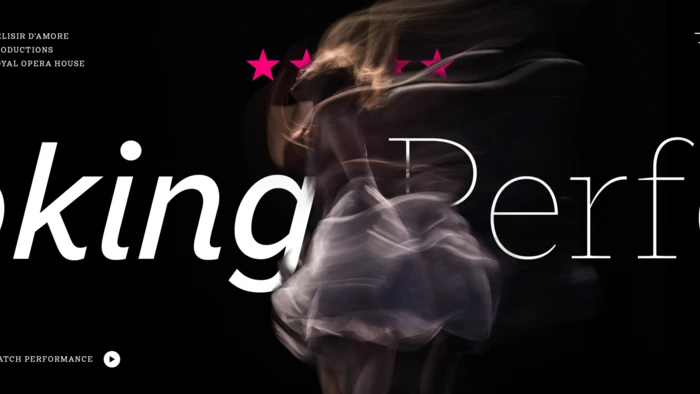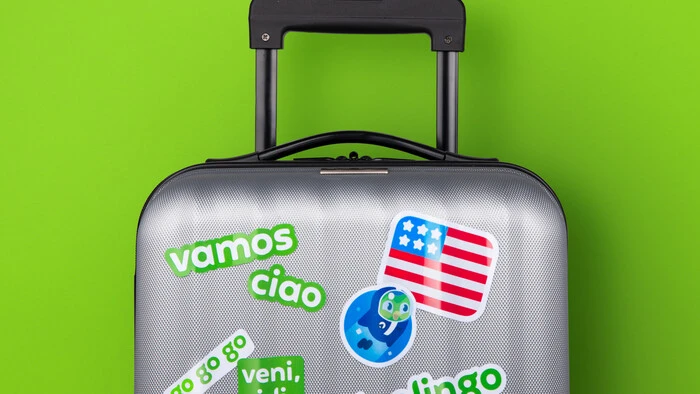
Lost and Foundry.
Fonts for good (des polices de caractères pour la bonne cause) : un projet de Fontsmith (faisant maintenant partie de Monotype Studio) et de M&C Saatchi, qui vise à imaginer une collection de polices de caractères s’inspirant des plaques de rues en mauvais état du quartier de Soho afin de collecter des fonds pour les sans-abri de Londres.
Amsteldok.
Une première mondiale : un logo en police variable pour WPP.
Dans la lignée novatrice et dynamique du nouveau format qu’est la police variable, Fontsmith (qui fait désormais partie du Studio Monotype) et l’agence de branding néerlandaise VBAT ont créé une police interactive pour le logo du nouveau campus de WPP à Amsterdam — un logo qui réagit aux mouvements et au temps. Lorsque les visiteurs se déplacent, les lettres font de même.
Duolingo.
Une police personnalisée distincte (et avec des ailes) pour Duolingo.
C’est en s’inspirant de Duo, l’iconique hibou vert de Duolingo, que l’agence Johnson Banks a commencé à explorer comment les formes de la mascotte pourraient influencer la typographie. Ensemble, nous avons étudié la manière d’intégrer les traits et l’esprit d’une aile de hibou dans une police de caractère personnalisée et donc unique.
Correos.
Correos, national postal service, is a brand of more than 350 years. Together with branding agency, Summa, we designed a new font exclusively for Correos, named Cartero (Postman) in honour of the emblematic professionals that has shaped the company since its early days.
MotoGP.
Nouvelle famille de typographies personnalisée pour le MotoGP™, la plus grande compétition de courses de motos sur route au monde.
Johan Cruijff ArenA.
Une police de caractères personnalisée pour la Johan Cruijff Arena d’Amsterdam et un logo pour symboliser « The Home of Legends »
Renault.
Deux polices personnalisées pour Renault : une police semi-sérif unique et une police de caractères gras italiques avec des majuscules uniquement.
Santander.
Dubai Font : une police de caractères d’avenir pour une ville et ses habitants
La ville de Dubaï s’est associée à Microsoft et Monotype pour créer une police de caractères qui reflète la nature énergique de Dubaï en caractères latins comme arabes.
Tencent étend ses frontières
Si vous utilisez une application de messagerie en Chine, il y a de fortes chances pour qu’elle appartienne à Tencent. Découvrez l’identité de marque et la police de caractères qui aident Tencent à s’étendre sur de nouveaux marchés.
Une police, 93 langues : le défi d’une création pour Sony
Le directeur typographe Akira Kobayashi a étroitement collaboré avec le directeur artistique en chef de Sony, Hiroshige Fukuhara, pour créer une police originale couvrant une centaine de langues environ.
Emilios Theofanous.
Né à Chypre, Emilios Theofanous, Directeur créatif exécutif chez Monotype, a un faible pour la typographie grecque et multilingue de qualité. Depuis qu’il a rejoint Monotype, il a travaillé sur plusieurs projets de polices exclusives et pour la bibliothèque Monotype. Avant Monotype, il a travaillé pour diverses fonderies internationales, ainsi que sur des projets à grande échelle tels que Source Serif Greek Italic pour Google Fonts et Adobe.
Akira Kobayashi.
Akira Kobayashi, directeur typographe, possède trois décennies d’expérience et une connaissance approfondie de la typographie japonaise, ainsi qu’une compréhension approfondie de la calligraphie. Après quatre ans d’études à l’université d’art de Musashino à Tokyo, Akira Kobayashi a commencé par travailler dans l’entreprise de composition photo Sha-Ken Co. où il s’est consacré au processus long et compliqué du design de caractères japonais.
Tom Rickner.
Tom Rickner est le Directeur principal, Solutions typographiques du Studio Monotype et sa carrière dans la typographie s’étend sur plus de trois décennies. Durant cette période, il a maîtrisé presque tous les aspects du design typographique et de la production de caractères, de l’édition de bitmaps à ses débuts au développement des toutes premières fontes multiples pour Adobe, en passant par les fontes variables TrueType GX pour Font Bureau et Apple.
Ryota Doi.
Ryota Doi est Directeur artistique créatif, team lead chez Monotype. Il s’est intéressé à cette discipline lorsqu’il a commencé ses études au Japon. Après avoir obtenu un Bachelor of Arts en design à l’université des arts de Tokyo, il s’est inscrit pour un Master en Typeface Design à la célèbre Université de Reading, où il a étudié les différences entre les caractères japonais et latins.
Ambiguity, une police et cinq personnalités
Monotype présente Ambiguity, une police de caractères conçue pour exprimer efficacement toute une série d’attitudes et d’opinions.